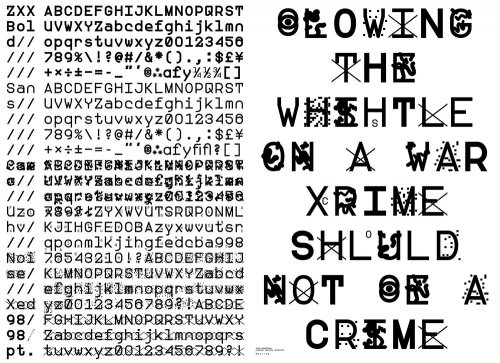
Создан шрифт, отпугивающий разведчиков США
Мир как-то не в восторге последнее время от разведки США. Она, похоже, читает переписку и подслушивает ни в чем невиновных (и местами виновных) граждан, объясняя это государственной необходимостью. Так или иначе, а разразившийся скандал побудил энтузиастов на создание самого разнообразного программного обеспечения для защиты от всевидящего правительства Штатов.
Впрочем, творческая мысль не дремлет, и помимо ПО был также разработан особый шрифт. По словам Санга Муна (Sang Mung), выпускника школы дизайна Род-Айленда, шрифт ZXX поможет более надежно защитить конфиденциальную информацию. Суть проекта в том, что ZXX крайне тяжело поддается расшифровке системами Агентства национальной безопасности. Впрочем, лишь пока. При желании, специалистам АНБ, скорее всего, не составит труда научиться читать и этот шрифт.